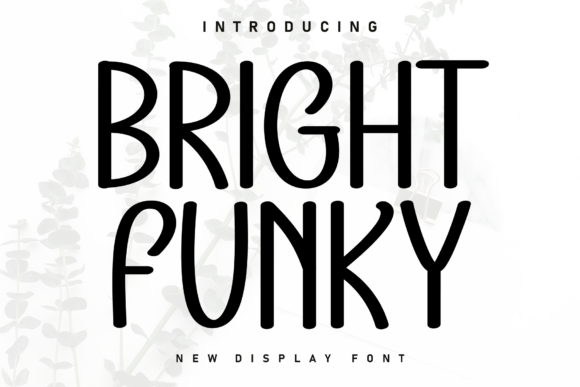
Bright Funky
Bright Funky – A Fonte Handwritten que Transforma seu Design
Se você está em busca de uma tipografia que una doçura e personalidade, Bright Funky é a escolha perfeita. Desenvolvida como uma fonte handwritten, ela traz caracteres que parecem dançar ao longo da linha de base, criando um efeito cozy e ao mesmo tempo vibrante. Ideal para projetos que precisam de um toque humano e acolhedor, Bright Funky destaca-se em convites, logos, embalagens e postagens de mídia social.
- Estilo único: Cada letra tem um leve balanço que confere movimento e energia ao texto.
- Versatilidade de uso: Funciona perfeitamente em cartões de visita, sites, revistas, e até em branding de produtos artesanais.
- Leitura agradável: Apesar do traço descontraído, a fonte mantém ótima legibilidade em tamanhos pequenos.
Com Bright Funky, seu projeto ganha um acento aconchegante que captura a atenção sem esforço. Experimente agora e descubra como essa fonte pode elevar a identidade visual da sua marca!